Colocando a IA para funcionar: A magia da combinação de fontes.
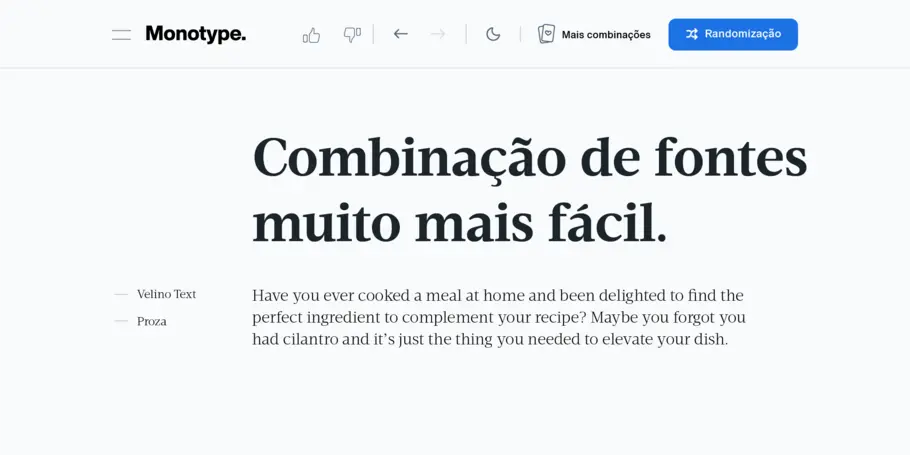
A combinação de fontes é uma prática subjetiva com infinitas possibilidades. Mas e se você tivesse uma ferramenta de IA que considerasse seus conhecimentos e emoções como seu assistente pessoal?
Você já preparou uma refeição em casa e ficou encantado ao encontrar o ingrediente perfeito para complementar sua receita?
Talvez você tenha se esquecido de que tinha coentro, amendoim triturado ou suco de limão, e isso é exatamente o que você precisa para dar mais sabor à sua refeição. Ou talvez você estivesse se vestindo para sair. Você escolheu seu jeans favorito, mas não tinha certeza de qual camisa combinaria. Você considerou como estava se sentindo e o local para onde ia. E, finalmente, decidiu colocar um suéter quente. Em qualquer cenário, você criou um sabor fresco e distinto, uma experiência aprimorada. E, como resultado, uma sensação de facilidade e satisfação tomou conta de você.
É assim que é encontrar a combinação de fontes perfeita.
O mecanismo de emparelhamento Monotype IA.
Essas são as decisões diárias que você toma sobre harmonia e contraste.
Essas combinações são designs bem pensados e cuidadosamente selecionados.
Assim como combinar qualquer coisa é uma prática subjetiva com infinitas possibilidades. Existem muitas escolhas boas, algumas ruins e outras excepcionais.
Agora imagine se tivesse uma ferramenta de IA que considerasse seus conhecimentos e emoções como seu assistente pessoal. Poderia oferecer ideias interessantes e encantadoras, e aumentar a velocidade e a qualidade de suas decisões criativas. Essas sugestões podem até funcionar como ressonância ou fonte de inspiração. Estamos usando a IA para aumentar a profundidade e amplitude de nossas sugestões de combinação de fontes.
O poder por trás da combinação de fontes.
Digamos que você esteja criando uma revista. Pode ser desejável ter uma paleta tipográfica muito flexível, com fontes sem serifa, capazes de lidar com tarefas de body copy. Um artigo poderia ter sans como corpo, e o próximo artigo poderia usar serifa para o corpo. Uma combinação eficaz como essa poderia oferecer variedade entre semelhanças.
A combinação de fontes expande sua paleta tipográfica, oferecendo mais opções de hierarquia, mais opções de textura e peso, bem como uma oportunidade de ajustar o tom de voz. Por exemplo, o conjunto de uma família sans pode ser adequado para lidar com a maioria das funções de fonte de uma marca. Mas poderia parecer mais amigável se você o combinasse com um estilo sans arredondado, talvez mais casual e pessoal se combinado com uma letra de mão, ou poderia até mesmo ser vestido em um tom mais sofisticado e sério, combinando-o com uma fonte serifada. Ao encontrar uma combinação de fontes exclusiva, você pode escolher sua primeira opção de fonte e transformá-la em uma aparência mais rara.
Algumas marcas e projetos podem funcionar com só uma única família de fontes. Mas uma segunda fonte pode adicionar muita flexibilidade e complexidade às suas mensagens. Também pode ser uma forma de ampliar ou atualizar uma marca existente. Talvez uma marca estabelecida esteja crescendo ao adicionar outro produto ou serviço que exija um tom diferente, mas que poderia se beneficiar por ter semelhanças visuais com o boom da marca-mãe e combinação de fontes para o resgate.
As combinações de fontes são extremamente valiosas; elas fornecem variedade, funcionalidade e tom de voz, gerando uma nova marca ou dando vida a uma marca antiga.
Como as fontes são combinadas: da harmonia ao contraste.
Uma grande variedade de combinações de fontes está disponível, variando de harmoniosas a contrastantes. Harmonioso significa que as coisas parecem semelhantes, combinam bem ou estão relacionadas por qualidades formais. Por exemplo, uma camisa azul com jeans azul, com uma pequena diferença de cor, teria harmonia. Uma camisa laranja com jeans azul teria muito mais contraste. O contraste consiste em enfatizar as diferenças.
Frequentemente, combinar uma sem serifa com outra sem serifa pode resultar em distinção insuficiente – muita harmonia e contraste insuficiente. Em vez disso, para uma paleta tipográfica mais sofisticada, muitos escolhem uma sans com uma serifa. Por exemplo, uma camisa azul com jeans azul pode parecer muito sem graça, oferecendo muita harmonia, mas uma camisa laranja pode ter muito contraste. É aí que o compromisso de usar uma cor análoga funcionaria melhor, como verde ou violeta, que são vizinhas do azul na roda de cores. Um pouco de contraste, mas principalmente em harmonia. O espectro de emparelhamento de fontes funciona como uma roda de cores dessa forma.
Os pares de fontes podem ser muito harmoniosos, especialmente estilos da mesma família, como Helvetica Now Regular e Bold, por exemplo. Eles combinam bem porque são muito semelhantes, com construção e proporções semelhantes, ao mesmo tempo que permitem algum contraste necessário para a hierarquia em qualquer layout. Simplificando, uma família de fontes é projetada para combinar consigo mesma; é por isso que projetamos tantos pesos em uma fonte. Uma “superfamília” como FF DIN ou Kairos ou Macklin, por exemplo, tem muitos estilos relacionados que são fáceis de combinar, como sans, serifa ou estêncil. Essas combinações prontas para uso são fáceis de escolher porque o nome da família indica que eles pertencem um ao outro.
Pares contrastantes podem ser quase qualquer coisa porque o foco está em como os estilos de fonte diferem. Algumas famílias de fontes foram projetadas como kits, em que o nome da família inclui sans e script, por exemplo, o que cria um modelo para o designer usar, como as famílias Charcuterie de Laura Worthington ou Ed’s Market. Esses são exemplos de combinações com maior contraste – eles parecem muito diferentes um do outro, mas criam um certo clima quando usados juntos.
Essa ferramenta fornece inspiração e insights sobre a arte da combinação de fontes, ao mesmo tempo em que auxilia na velocidade e qualidade de suas escolhas de fontes. Não é por acaso. Isso funciona. É fonte, tecnologia e experiência ao apertar um botão.